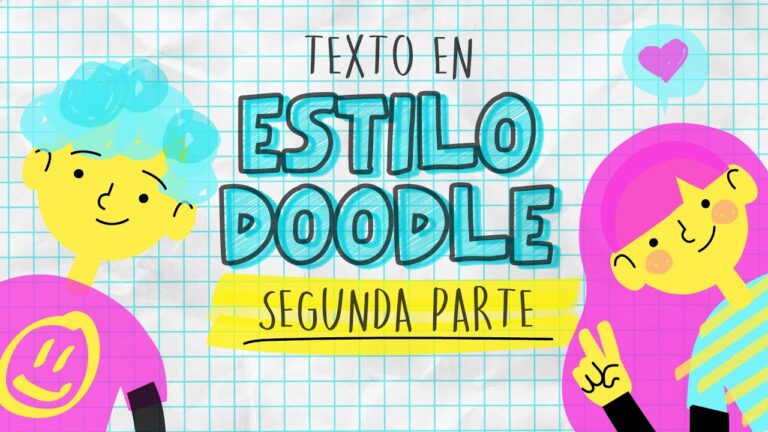
Estrategias Efectivas para Destacar la Tipografía en tu Portafolio
En el competitivo mundo del diseño, la tipografía no solo es un elemento funcional, sino una poderosa herramienta de comunicación visual. Saber cómo aplicar estrategias para destacar la tipografía en un portafolio puede marcar la diferencia entre ser recordado o pasar desapercibido. Este artículo explorará técnicas prácticas que no solo realzan la estética de tus proyectos, sino que también transmiten tu estilo personal y profesional, asegurando que tu trabajo brille con luz propia.
¿Cómo resaltar la tipografía en tu portafolio?
Utiliza contrastes de color, juega con tamaños y estilos, y asegúrate de mantener la legibilidad. Incorpora ejemplos variados y utiliza espacio en blanco inteligentemente.
¿Cuáles son las cuatro normas de la tipografía?
La tipografía es un arte que se rige por cuatro reglas fundamentales que garantizan una comunicación práctica y estética. Primero, la legibilidad es vital; se debe seleccionar un tipo de letra que sea fácil de leer a diferentes tamaños. Segundo, el contraste juega un papel importante; combinar colores y pesos de fuente de manera adecuada asegura que el texto destaque. Tercero, el espaciado, tanto entre letras como entre líneas, debe ser equilibrado para facilitar la lectura y mantener la armonía visual. Por último, la coherencia tipográfica ayuda a establecer una identidad clara, utilizando un conjunto limitado de fuentes que se complementen entre sí en el diseño. Estas reglas son esenciales para lograr un resultado tipográfico atractivo y funcional.
¿Cuál es la tipografía y cuáles son sus cinco reglas más importantes?
La tipografía es el arte y la técnica de organizar letras y símbolos para crear un texto legible y estéticamente agradable. Su importancia radica en que no solo se trata de elegir una fuente adecuada, sino también de cómo se presenta esa fuente en diferentes contextos. Una buena tipografía puede mejorar la comunicación visual, atraer la atención del lector y transmitir la personalidad de una marca o mensaje.
Existen cinco reglas fundamentales que todo diseñador debe considerar al trabajar con tipografía. En primer lugar, la elección de la tipografía debe ser coherente con el tono del contenido; por ejemplo, una fuente elegante para una invitación formal. En segundo lugar, es vital mantener una jerarquía visual clara, utilizando diferentes tamaños y estilos para guiar al lector a través del texto. Además, el espaciado entre letras y líneas debe ser equilibrado para garantizar una lectura fluida.
Por último, el contraste es esencial para destacar elementos importantes y mejorar la legibilidad. Utilizar colores y tamaños que se diferencien adecuadamente del fondo es fundamental. Por último, es recomendable limitar el número de fuentes utilizadas en un diseño para evitar confusiones. Siguiendo estas reglas, se puede lograr una tipografía práctica que no solo comunique el mensaje deseado, sino que también capte el interés del público.
¿Cómo se realiza el diseño tipográfico?
El diseño tipográfico es un arte que combina creatividad y técnica, y comienza con la elección de la tipografía adecuada que refleje el mensaje y la personalidad del proyecto. Es esencial considerar la legibilidad y la jerarquía visual, utilizando tamaños y estilos que guíen la atención del lector de manera práctica. La alineación y el espaciado también juegan un papel vital, ya que un buen uso del espacio en blanco puede realzar la composición. Además, experimentar con la combinación de diferentes fuentes y colores puede aportar dinamismo, pero siempre debe hacerse con un enfoque equilibrado para mantener la armonía visual. Al final, un diseño tipográfico exitoso no solo comunica información, sino que también genera una conexión emocional con el espectador.
Resalta tu Estilo: Claves para una Tipografía Impactante
La tipografía es el alma de cualquier diseño, y elegir las fuentes adecuadas puede transformar un mensaje común en uno memorable. Opta por tipografías que reflejen la personalidad de tu marca y asegúrate de que sean legibles en diferentes tamaños y plataformas. Juega con el contraste entre estilos, como combinar una fuente serif elegante con una sans-serif moderna, para crear un equilibrio visual atractivo. No olvides considerar el espaciado y la alineación, ya que estos elementos pueden mejorar la fluidez de la lectura y guiar la atención del espectador. Con estas claves, podrás resaltar tu estilo y hacer que tu comunicación sea realmente impactante.
Diseño que Atrae: Mejora tu Portafolio con Tipografía
La tipografía es un elemento clave en el diseño que puede transformar un portafolio ordinario en uno extraordinario. Al elegir las fuentes adecuadas, puedes comunicar tu personalidad y estilo de manera práctica, capturando la atención de tus potenciales clientes. Una combinación armoniosa de tipografías puede crear jerarquía y claridad, lo que facilita la navegación y la comprensión del contenido.
La selección tipográfica no solo se trata de estética; también influye en la percepción del mensaje que deseas transmitir. Fuentes elegantes y modernas pueden evocar sofisticación, mientras que tipografías más divertidas y creativas pueden reflejar un enfoque innovador. Es fundamental que la tipografía elegida esté alineada con tu marca personal y el tipo de proyectos que deseas atraer, creando así una conexión auténtica con tu audiencia.
Finalmente, no subestimes el poder del espacio en blanco y la legibilidad. Un diseño bien equilibrado que utiliza correctamente el espacio disponible permite que la tipografía brille sin abrumar al espectador. Al mejorar tu portafolio con una tipografía bien pensada, no solo haces que tu trabajo destaque, sino que también dejas una impresión duradera que puede abrir puertas a nuevas oportunidades.